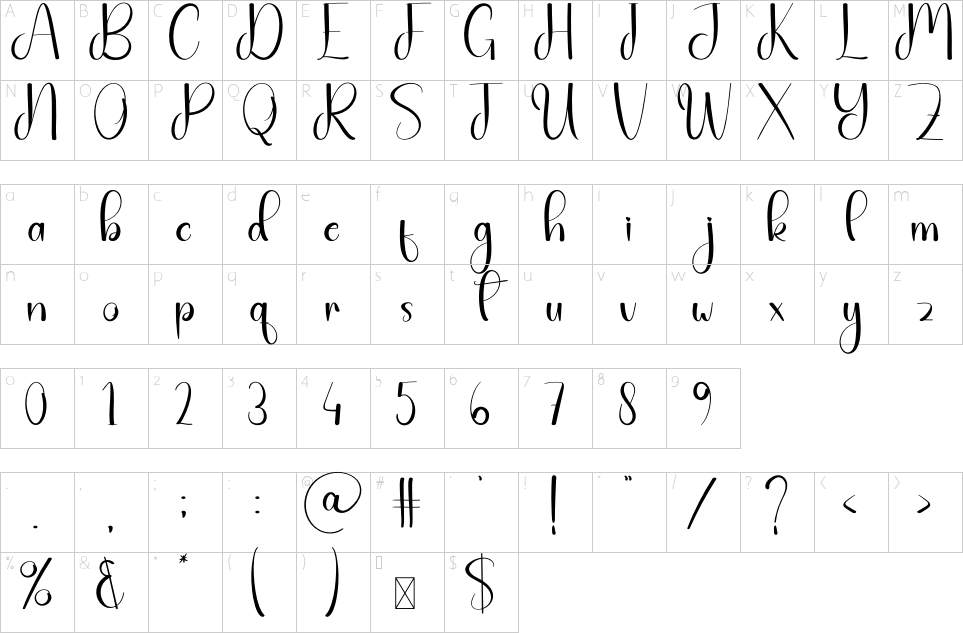
A fonte Amster Night é um prato extra para seu projeto de design, especialmente para quem busca um visual moderno e elegante. Desenvolvida por scratchones, esta fonte oferece uma paleta vibrante e sofisticada que se adequa perfeitamente para criações de design gráfico, desde logotipos até materiais de marketing. Com uma interface intuitiva e fácil de usar, a Amster Night font é perfeita para quem busca uma solução de fonte acessível para projetos em Windows e Mac. Foram 596 usuários que já experimentaram a versão gratuita desta fonte, provando sua eficácia e qualidade. Com Amster Night, você pode criar designs que chamam a atenção, seja no seu site, aplicativo ou qualquer projeto digital que precise de uma fonte moderna e atraente. Experimente e descubra por si mesmo por que muitos designers estão sequestrando esta fonte.